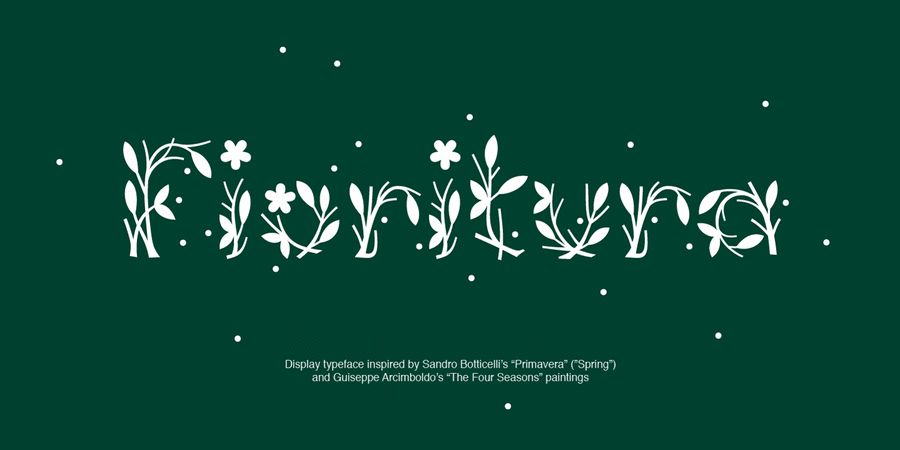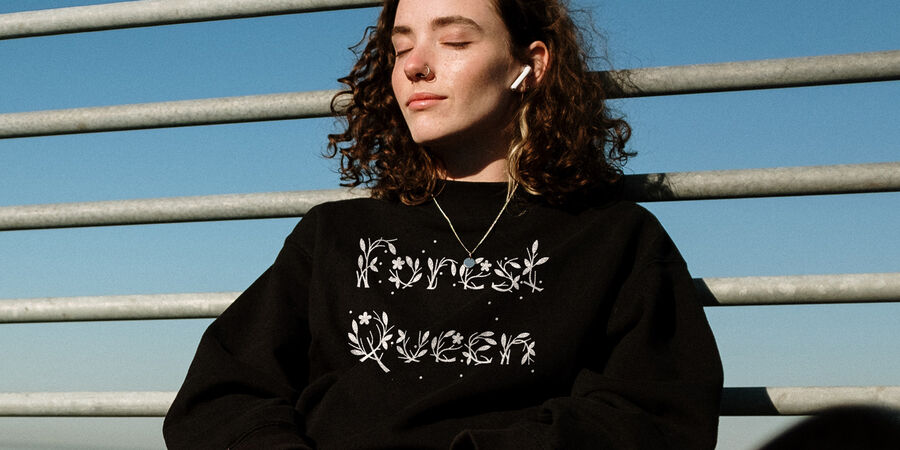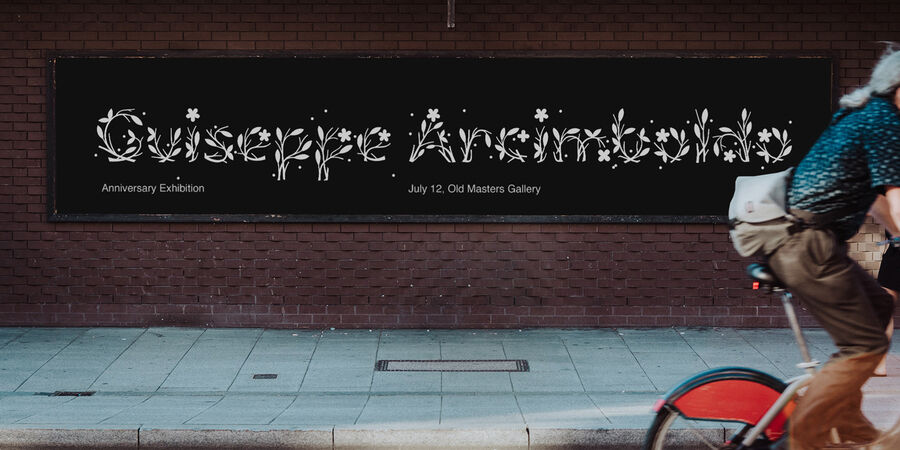
Fioritura (1 шрифт)
Fioritura — це квітучий весняний шрифт, натхненний картинами Сандро Боттічеллі "Primavera" ("Весна") і Джузеппе Арчимбольдо "Чотири пори року". Fioritura в перекладі з італійської означає розквіт або цвітіння, а композиція літер складається зі стебел, листя, квітів і летючого пилку.
Шрифт розробив Михайло Рафайлик у 2022 році.